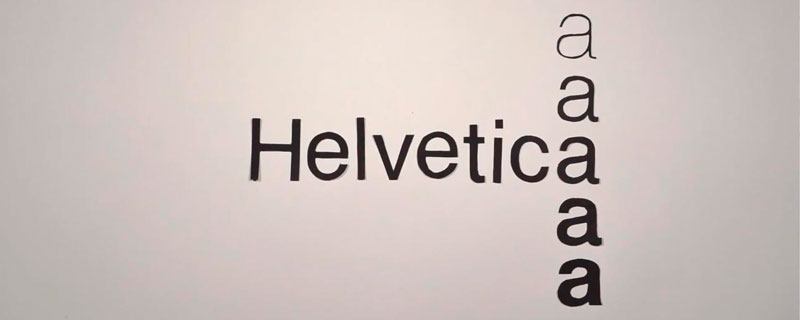
Ben ha hecho un stop-motion sobre la historia de la tipografía, todo con recortes de papel en blanco, negro y rojo y la expresión que consigue con sus manos.
En el vídeo se explica el origen desde las blackletters de Guttenberg, pasando por la Helvética hasta las tipografías fantasía que se pueden hacer desde el ordenador.